Schlussstück
»Schlussstück« ist ein typografischer Fachbegriff aus dem gewerbespezifischen Sprachschatz dspr. Schriftsetzer, Schriftgießer und Drucker aus der Periode des materiellen Schriftsatzes mit physischen Drucktypen aus Metall (z.B. aus einer Blei-Zinn-Antimon-Kupfer-Legierung), Holz (z.B. aus Birnbaumholz) oder Kunststoff (z.B. aus Kunstharz). Der Begriff bezeichnet ein gegenständliches oder abstraktes Alinea (Schmuckzeichen), das eine Textpassage oder ein Kapitel eines Buches grafisch abschließt. Alternativ kann es als typografischer Zierrat (typografischer Schmuck) oder Vignette (Rebranke) am Ende einer Kolumne verwendet werden. Alternative Schreibweise: »Schlußstück«.
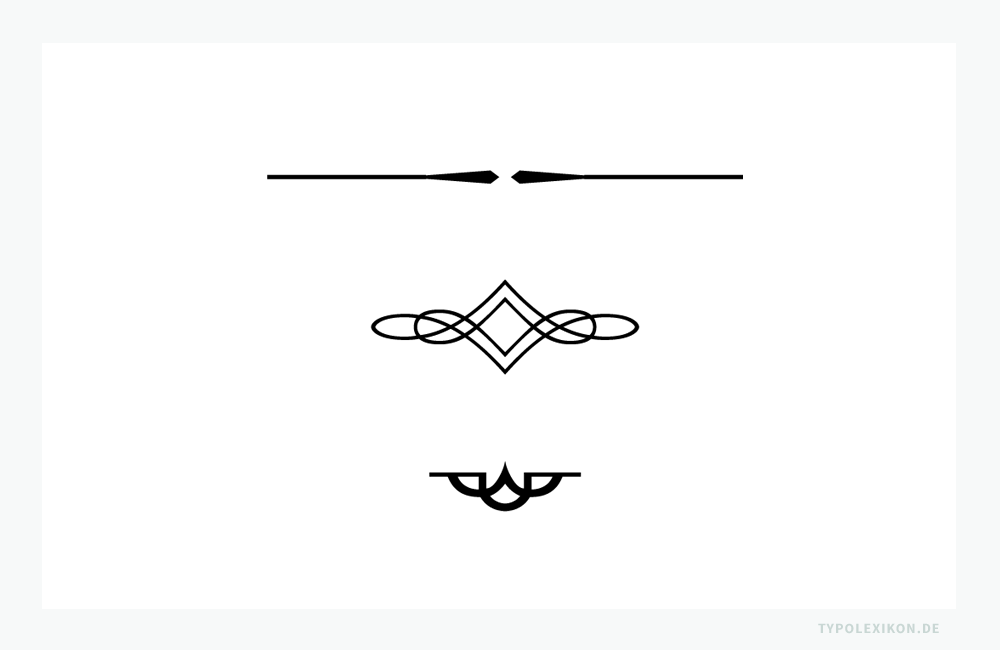
Schlussstücke können unterschiedliche Formen, Größen und Symmetriearten 1) aufweisen und besitzen in der Regel keinen direkten semantischen Bezug zum Text. Sie dienen primär als illustratives Gliederungselement. Die Formvielfalt reicht von Drei-Sterne-Abschlüssen über verzierte Linien (Schlusslinien) und Englische Linien bis hin zu figürlichen Ornamenten und Vignetten. Während der kunstgeschichtlichen Epoche des Jugendstils war beispielsweise die »Kalliope« ein häufig verwendetes Schlussstück. Eines der bekanntesten Zierzeichen dieser Art in der europäischen Typografie ist das »Aldusblatt« 2) , das auf den venezianischen Typografen Aldus Manutius (1449–1515) zurückgeht.
Im Schriftsatz mit physischen Drucktypen aus Metall gehörten Schlussstücke zum »Zierrat« und wurden in der Regel gemeinsam mit den Akzidenzschriften aufbewahrt. 3) Schriftgießereien boten während der Epoche des Handschriftsatzes eine Vielzahl an Formen an, die sich an den jeweiligen Kunststilen und typografischen Moden orientierten.
Bei gut ausgebauten OpenType Fonts finden sich oft einige wenige Alineas im erweiterten Zeichensatz eines Fonts. Beispielsweise verfügt die Französische Renaissance-Antiqua »Minion Pro« von Robert Slimbach (*1956) über mehrere speziell gestaltete Schlussstücke, die stilistisch zur Anmutung dieser Schrift passen. Zudem bieten Schriftanbieter spezielle Symbol Fonts an, die ausschließlich Schlussstücke, Alineas und Vignetten in verschiedenen Designs enthalten. Ein bekanntes Beispiel ist die Linotype Decoration P1, deren Zeichentabelle rund 84 Figuren umfasst. 4)
Schlussstücke werden im modernen Buchsatz nur noch selten verwendet.
| ↑1 | Anmerkung: Symmetriearten sind beispielsweise die Achsensymmetrie, die Zentralsymmetrie und die Asymmetrie. |
| ↑2 | Anmerkung: In der Kalligraphie als »Hederablatt« bezeichnet. |
| ↑3 | Anmerkung: In einigen typografischen Lehrbüchern wird darauf hingewiesen, dass Vignetten nicht zum Zierrat zählten (Beispiel: Luidl, Philipp: Typografie, Herkunft, Aufbau, Anwendung. Schlütersche Verlagsanstalt und Druckerei, Hannover, 1984, ISBN 3-87706-212-1, Seite 51). Wahrscheinlicher ist jedoch, dass Offizinen die Klassifikation und Aufbewahrung von Vignetten unterschiedlich handhabten, was vermutlich mit der Größe der Druckerei und dem Spezialisierungsgrad ihrer Satzabteilung(en) zusammenhing. |